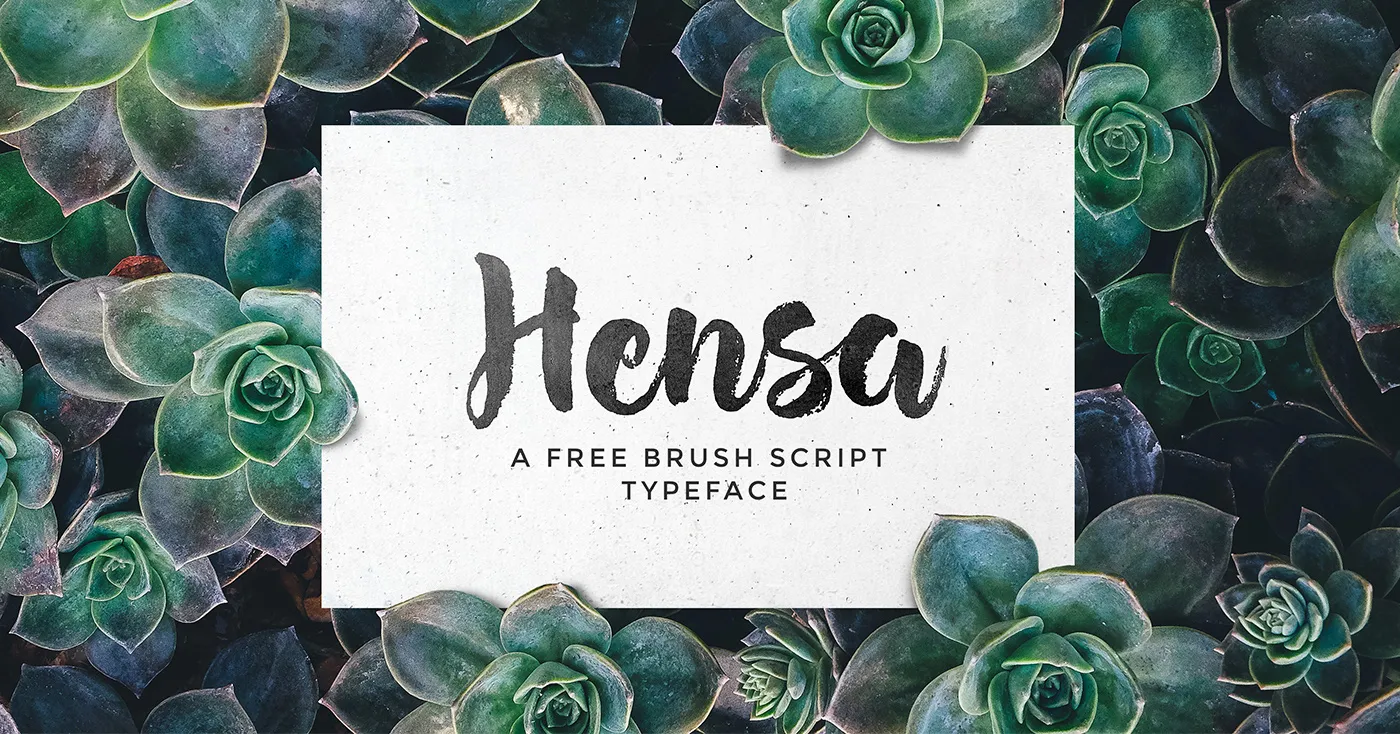
Hensa Brush Font – Download Grátis
A fonte ‘Hensa Brush’ foi projetada por Vlad Cristea e compartilhada pela Graphicburger sem consolidar os direitos autorais. Esta elegante fonte brush é perfeita para adicionar um toque criativo aos seus trabalhos de design. A sua tipografia fluida e alegre combina bem com qualquer projeto, seja ele gráfico ou digital. Ideal para criações que precisam de uma aparência relaxada e despojada, Hensa Brush oferece flexibilidade suficiente para diferentes formatos e tamanhos de texto. Uma excelente escolha para aquelas propostas que buscam um ar descontraído sem sacrificar a qualidade da escrita.